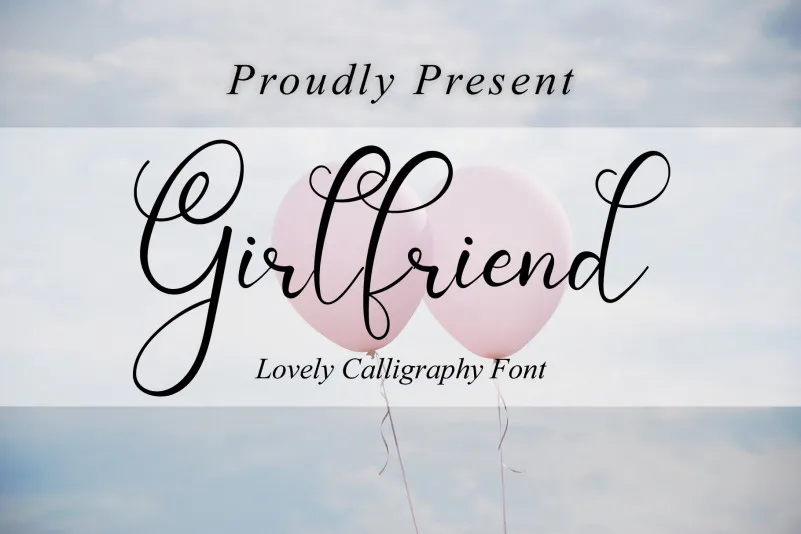
A fonte Girl Friend é uma escolha elegante para projetos delicados e inspiradores. Com seu traço fino e fluido, esta font foi criada com um toque refinado que certamente encaixa-se perfeitamente em seus trabalhos favoritos. Seu charme suave se destaca em uma ampla gama de ideias de design, tornando-a uma escolha perfeita para adicionar um toque alegre e romântico aos mais diversos projetos. A Girl Friend Font é ideal tanto para aqueles que buscam uma fonte delicada quanto para quem procura algo que traga leveza e romantismo ao seu trabalho, seja ele o design de revistas, ilustrações, ou letras douradas nas paredes da sua casa. Não deixe de experimentar esse toque suave e elegante em suas próximas criações!